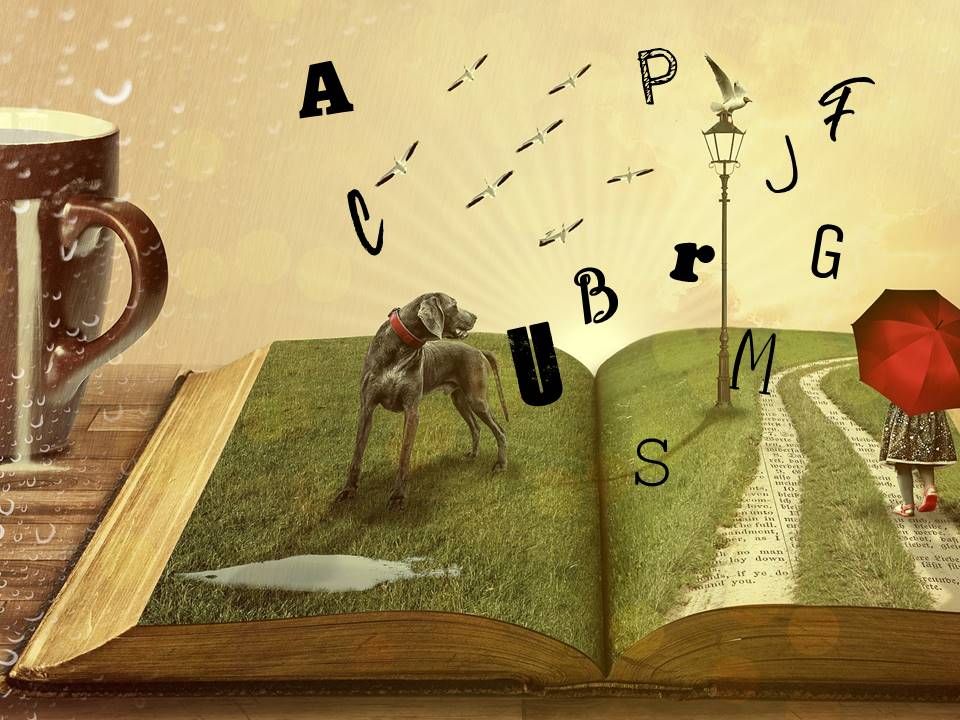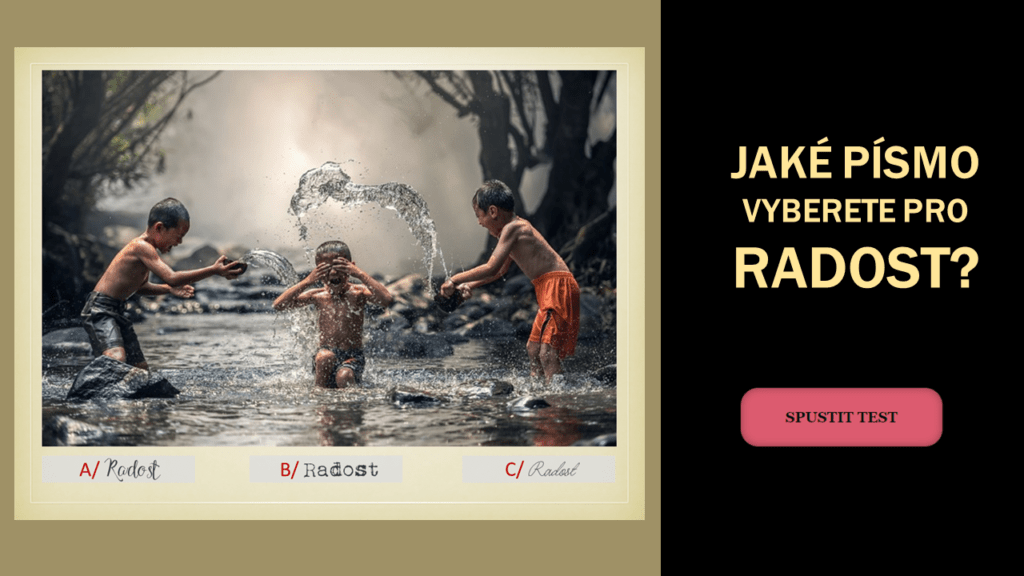
Vdechněte svým textům duši
Je jedno kam font vybíráte. Je jedno, pro koho font vybíráte. Ale jsou věci, které musíte vědět, abyste vybrali font, který funguje.
Máte na výběr tisíce fontů ve fotobankách, ale stejně netušíte, jaký vybrat? Vyfiltrujte si je třeba podle ideálního klienta.
Pomůžu vám vybrat písmo, které podpoří vaše podnikání. A možná zjistíte, že si odnesete daleko víc než vybraný font.
PROČ PSYCHOLOGIE FONTŮ?
„U každého slova, které čteme, vnímáme nejenom jeho obsah, ale i formu. Proto jsou fonty velice důležitou součástí celkového designu i značky. Velmi často podceňovanou.“
Fonty jsou velice důležitou součástí celkového designu, stejně jako například barvy. Forma by vždy měla ladit s obsahem.
Font sám o sobě má obrovskou moc ovlivnit vnímání čtenářů a tím i to, jestli vám budou věřit nebo ne.
Font je nedílnou součástí vizuální identity firmy či podnikatele a stojí za to si ho vybrat s jasným záměrem.
Fonty dokonale odráží to, jací doopravdy jste. Popíšou váš charakter, hodnoty i nastavení vůči druhým.
který vám ukáže, že není font jako font.
„Jako webdesignerka se setkávám s výběrem fontů velmi často. Vždy jsem k nim přistupovala obezřetně a s respektem, ale spíše tak, abych nevhodným fontem "nepokazila" celkový design webu. V grafice mám ráda čistotu a minimalismus, takže jsem v 90% případů skončila u jednoduchých bezpatkových fontů. Ty totiž nikoho neurazí, ale ani nenadchnou... Až díky Andree jsem objevila, jak velký rozdíl může udělat font "na míru" s designem a celkovou náladou webu.“
„Font, použitý na webu nebo na vizitce, vyjadřuje osobitost, ovlivňuje vnímání a dokresluje celkový dojem. Má moc přitáhnout ty správné klienty a odradit ty ostatní. Dovoluje vyjádřit atributy, jako je důvěra, jednoduchost, péče, něžnost nebo síla. Proto dává smysl věnovat volbě fontu stejnou pozornost jako výběru barev, ilustračních fotografií nebo sloganu. A proto považuji psychologii fontů za velmi užitečný marketingový nástroj.“
Hledáte font a netušíte, jestli vybrat patkový, bezpatkový nebo ručně psaný? A vůbec, co jsou to ty…
"Prosím tě, jaké fonty v Canvě píšou česky, já z toho už asi rozkvetu!" Jsou lidé, kteří…
Někdo to vůbec neřešíte, někteří z vás to řeší až moc. A protože výběr fontu je můj denní…